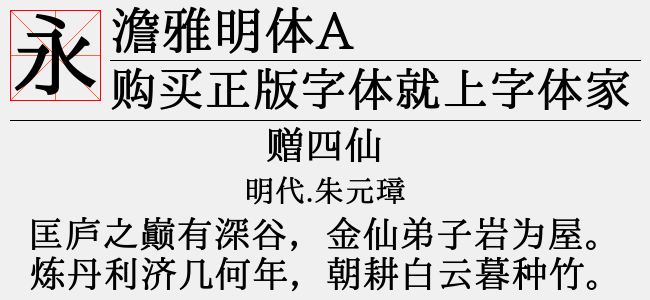
澹雅明体A(23.55 MTTF中文字体下载)
澹雅明体A 字体大小23.55 M,包含了6763个汉字以及附加其他英文字体和阿拉伯数字,属于佚名。澹雅明体A(TTF)可以免费下载,免费商用,它的特征就是印刷,明体,公文,免费商用,新愚公系列,采用安装嵌入的安装方式,支持符号拉丁文日文中文等语言
字体名称:澹雅明体A